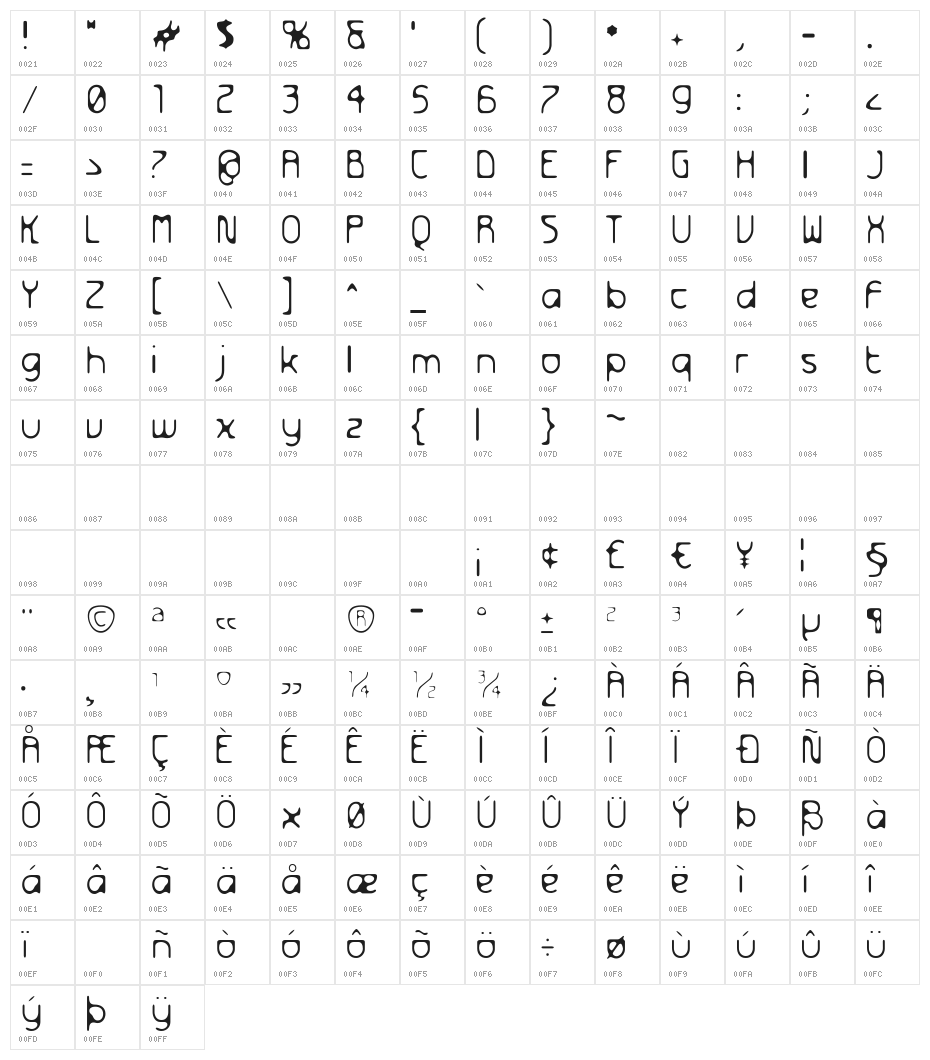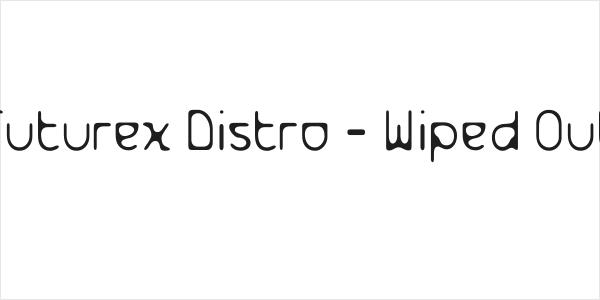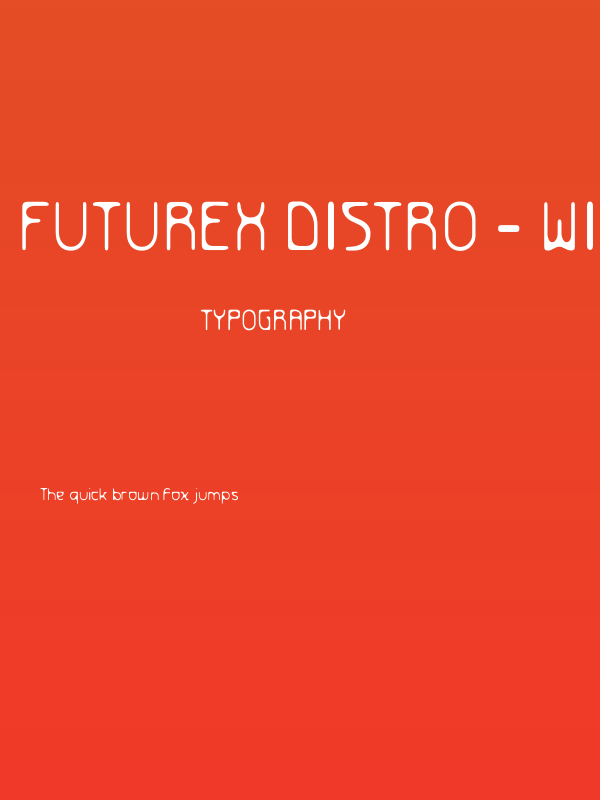
Futurex Distro - Wiped Out Font
| Vorgeschlagene Projekte | Ideal for children's books, playful branding, creative posters, and unique packaging designs. |